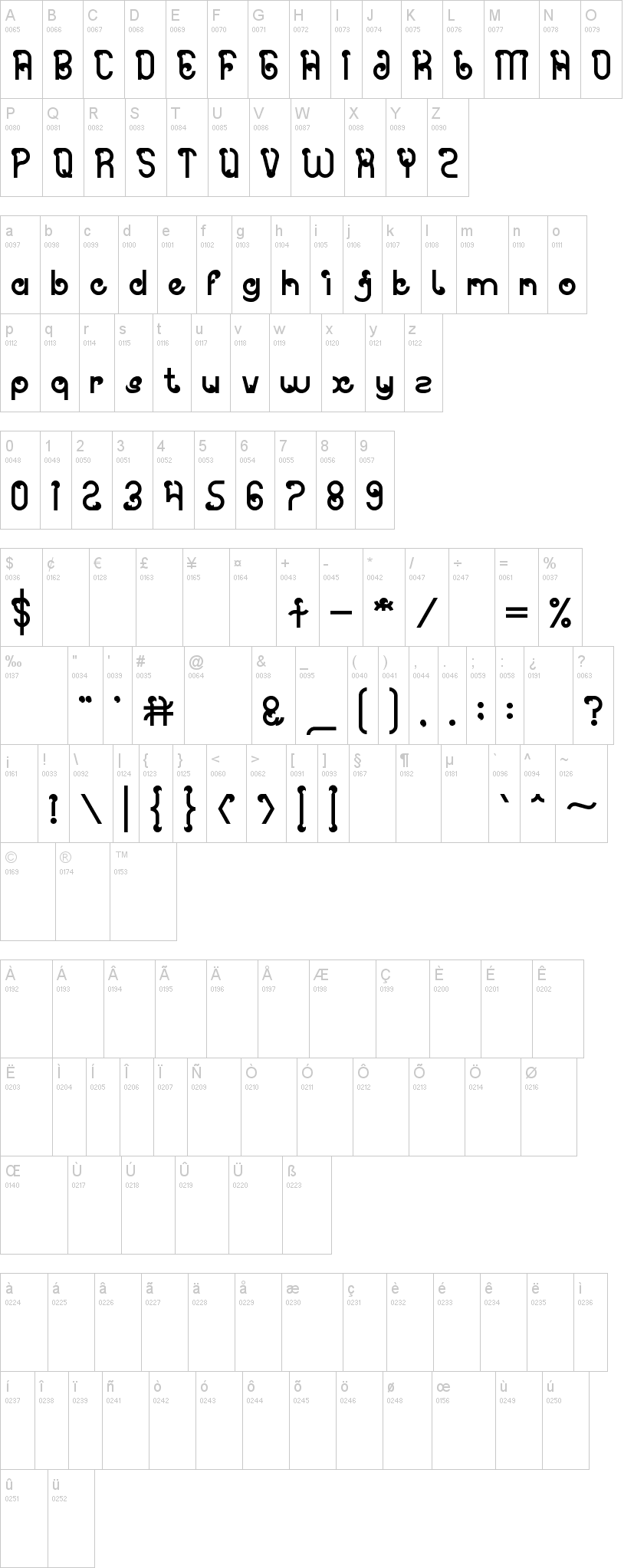
Spicy Paprika
? Spicy Paprika 字体是一款设计师非常喜爱的手写字体,它具有温暖、活泼的外观,能够提供清新、活力的视觉效果,适合用于各种类型的设计项目,尤其是用于创造活泼、充满活力的设计效果。它具有自然的曲线和灵活性,能够满足用户对字体的不同需求,同时也具有良好的可读性,可以让用户更好地理解文本内容。
Spicy Paprika是一款非常不错的手写艺术字体,具有很好的视觉感,适合于文化类的宣传设计、商业类品牌的广告和产品包装设计以及个性化文字排版等较多场景。
Spicy Paprika字符映射图